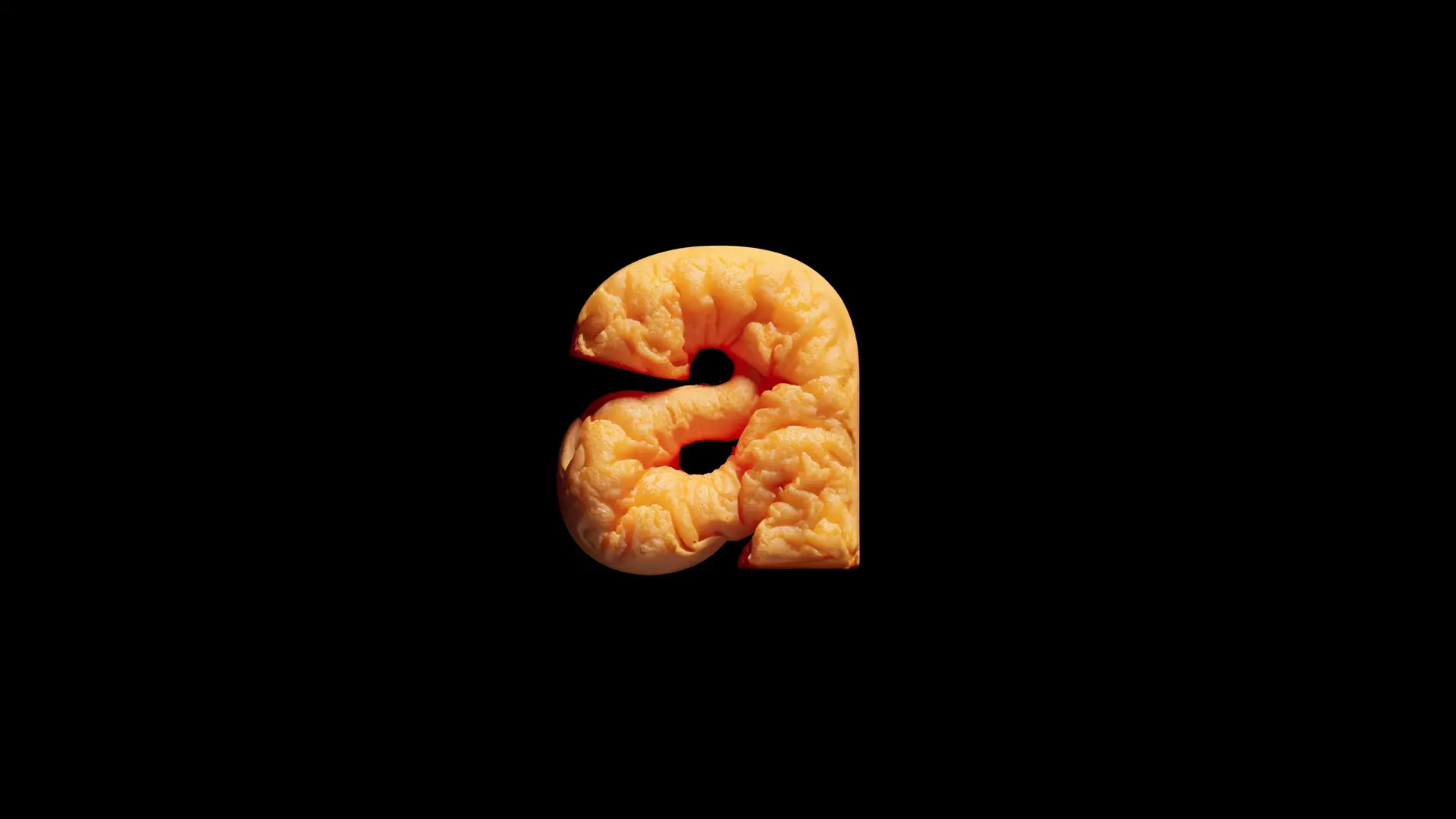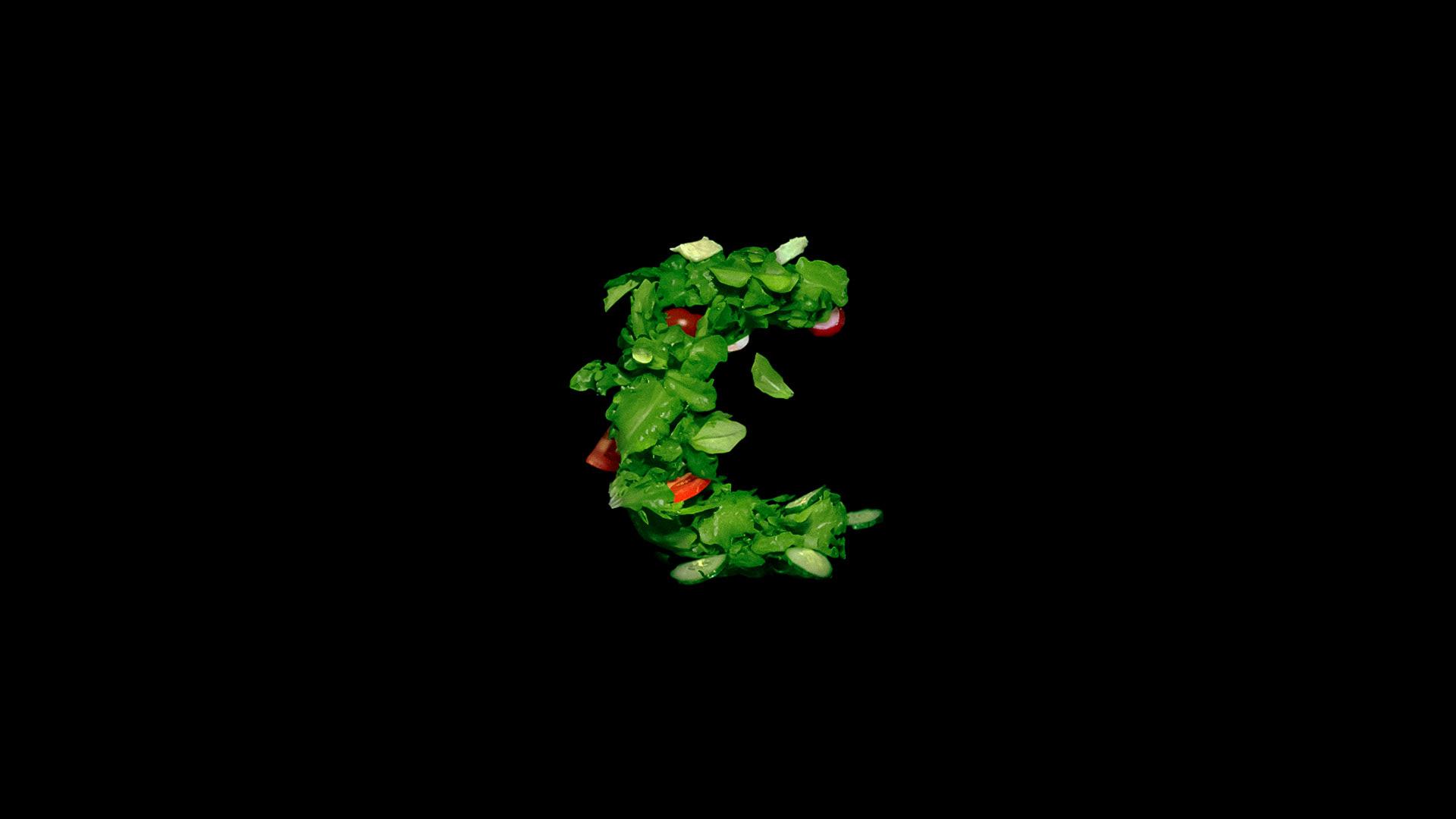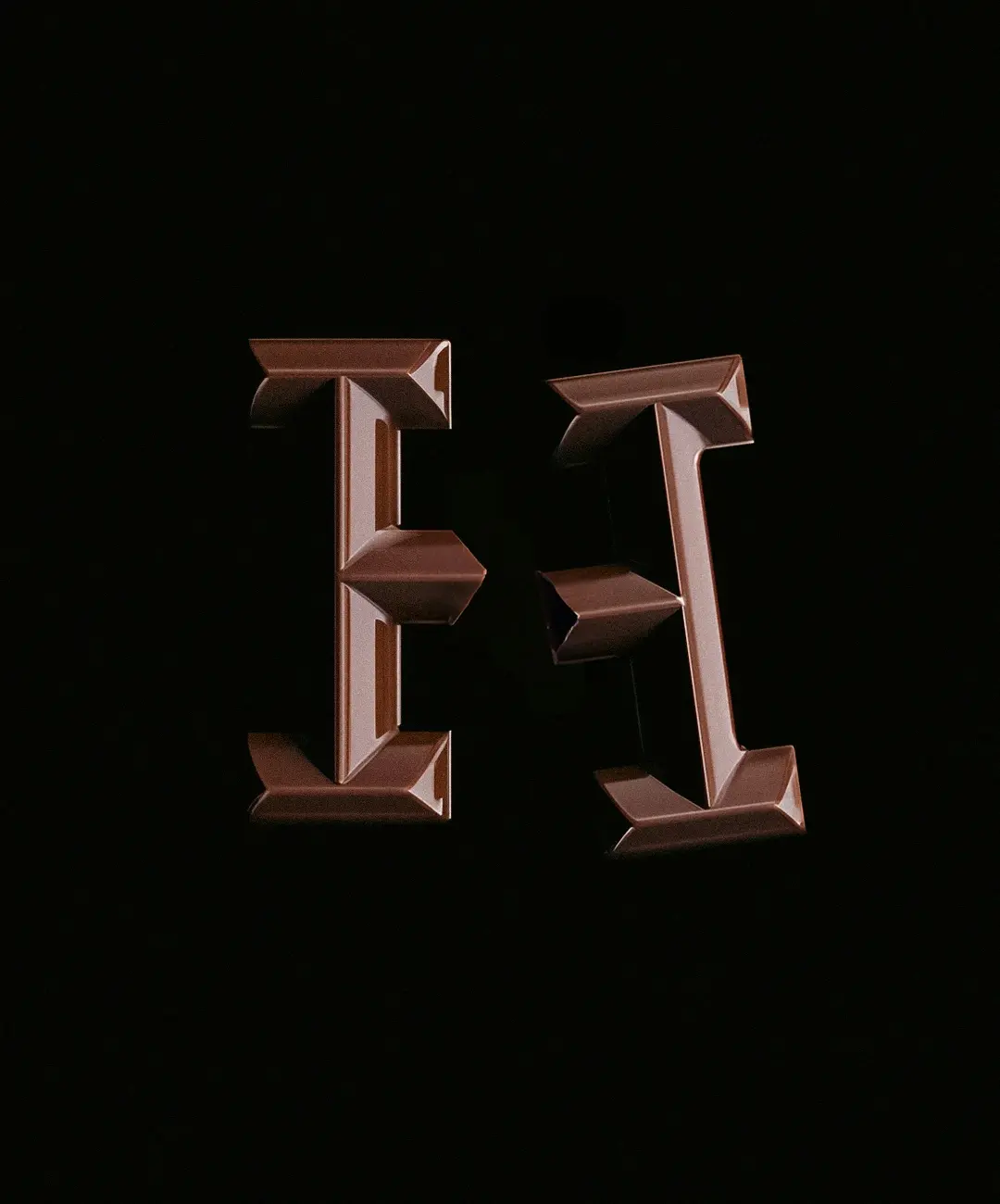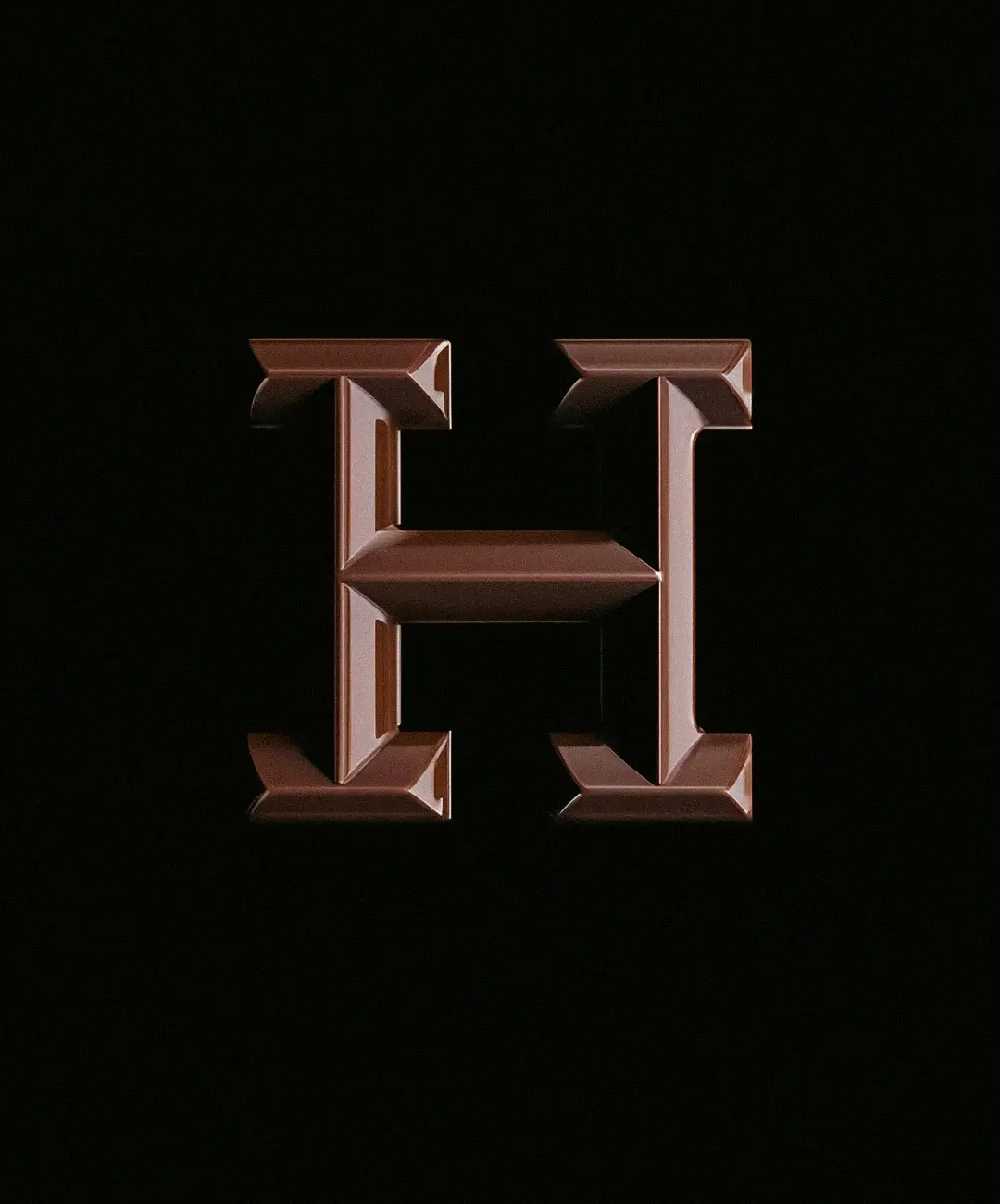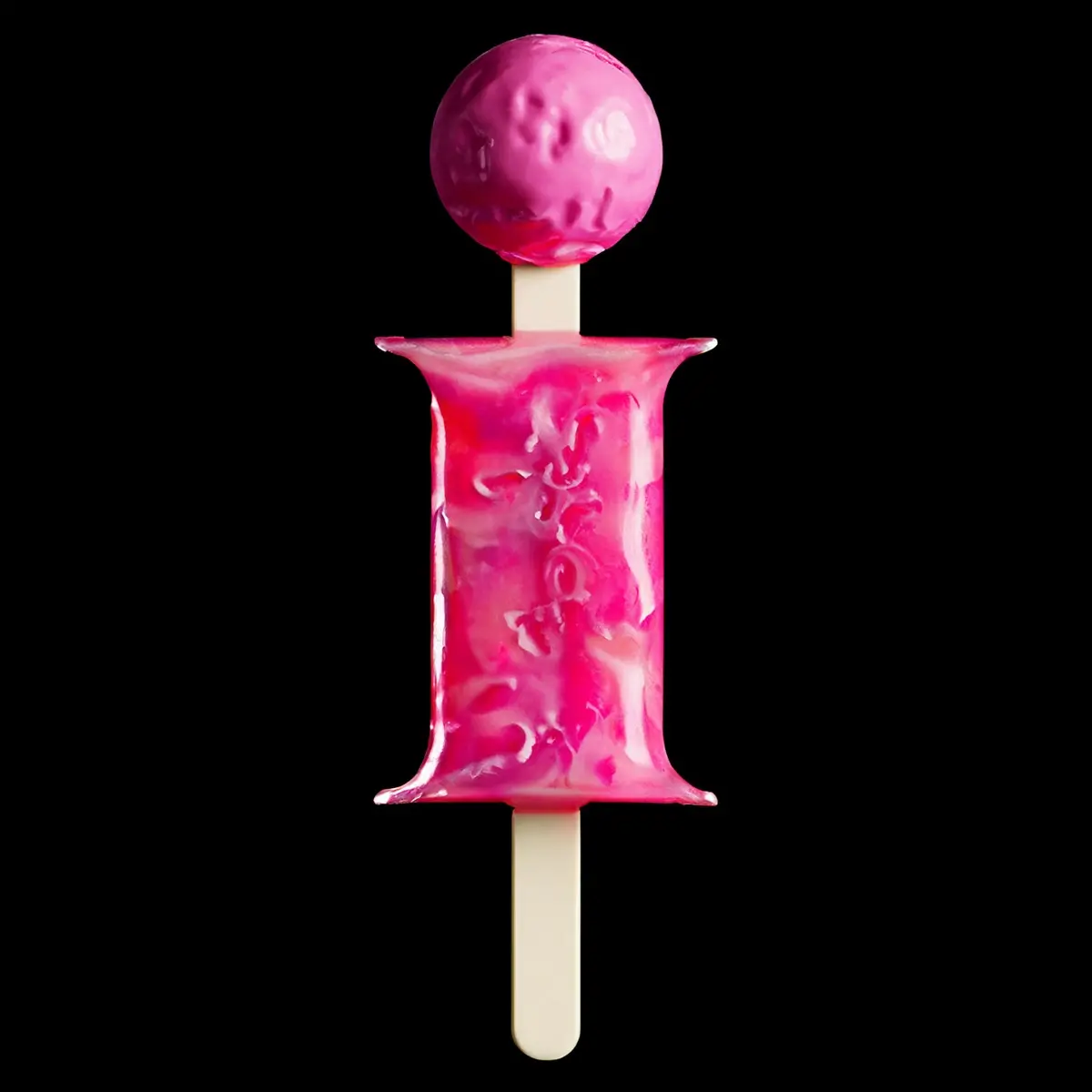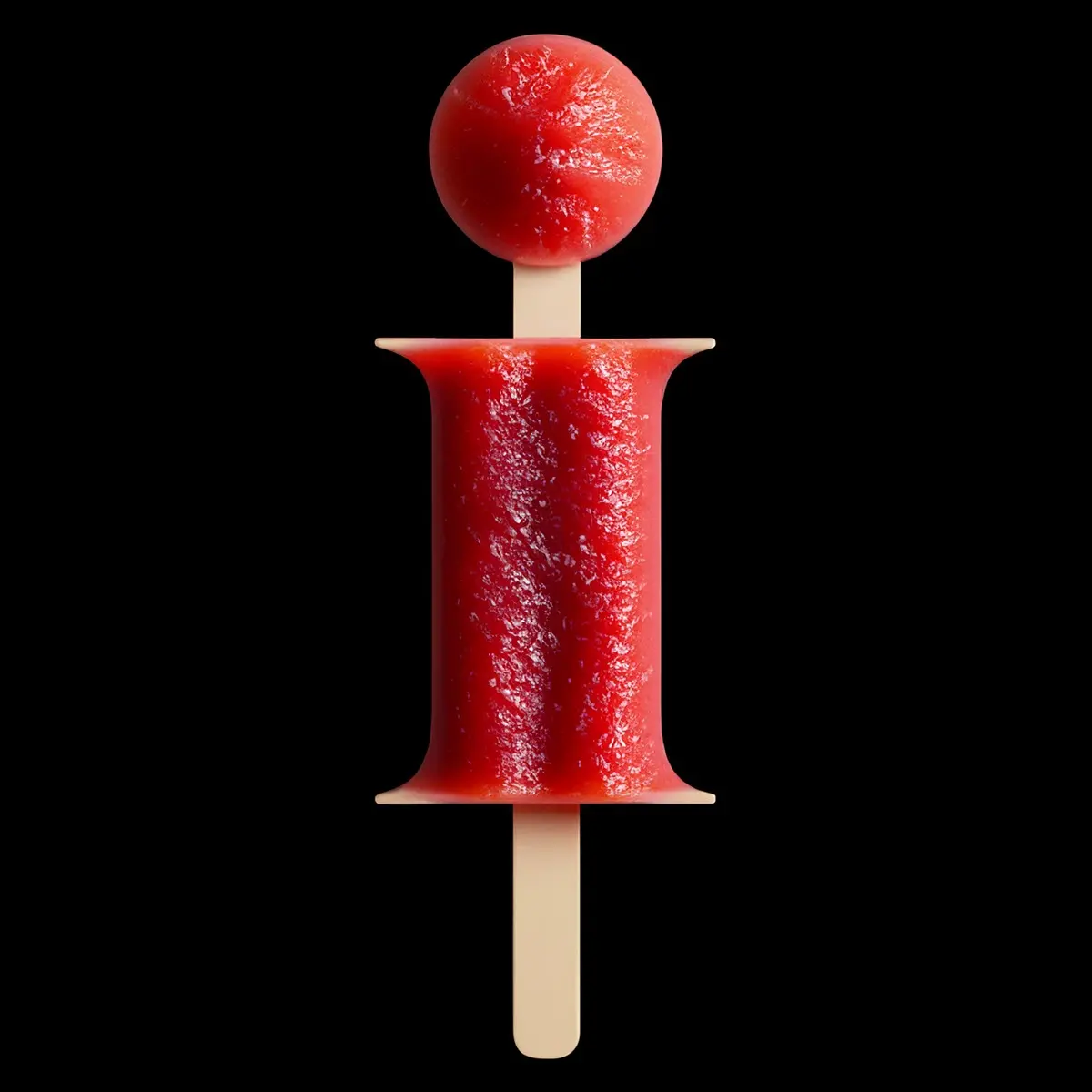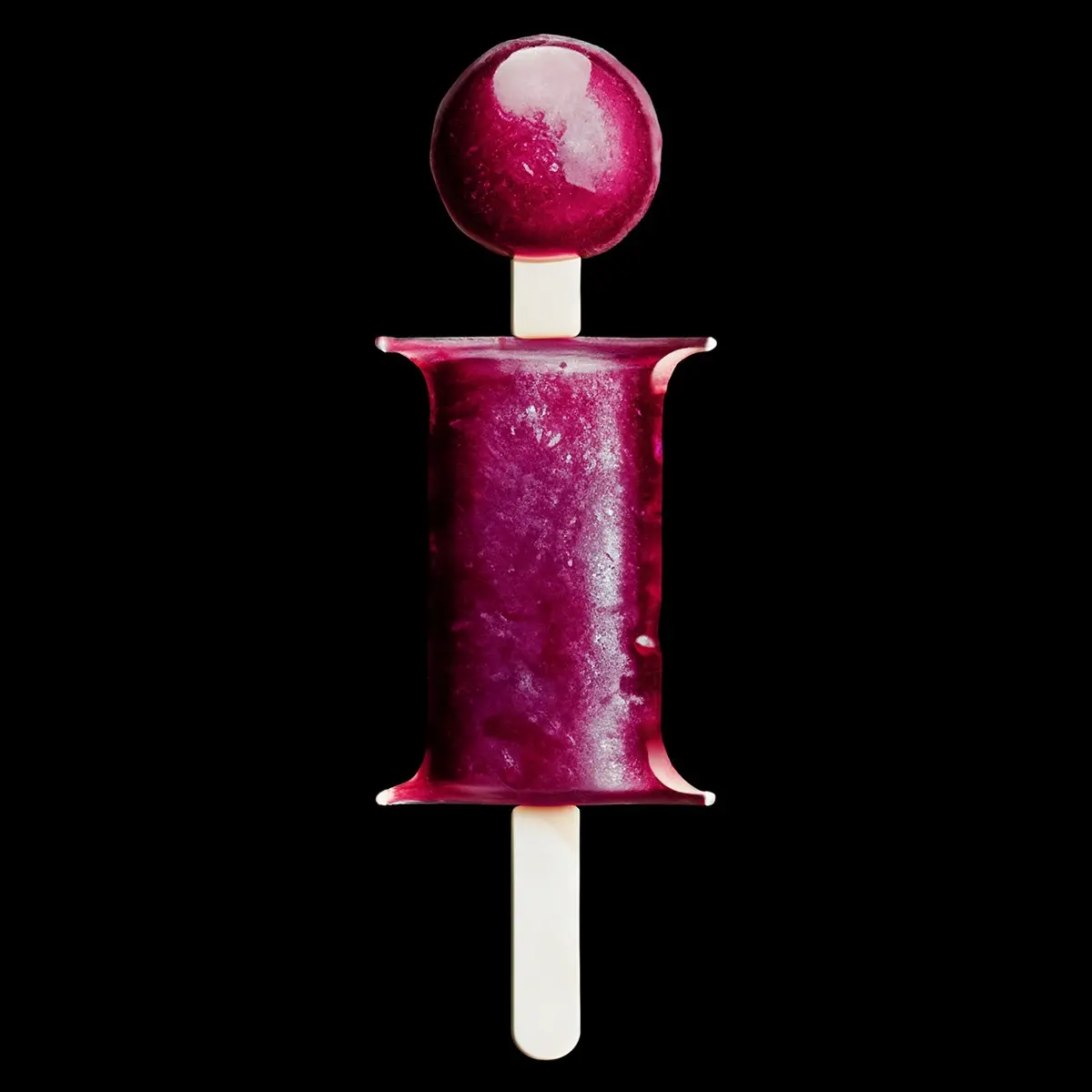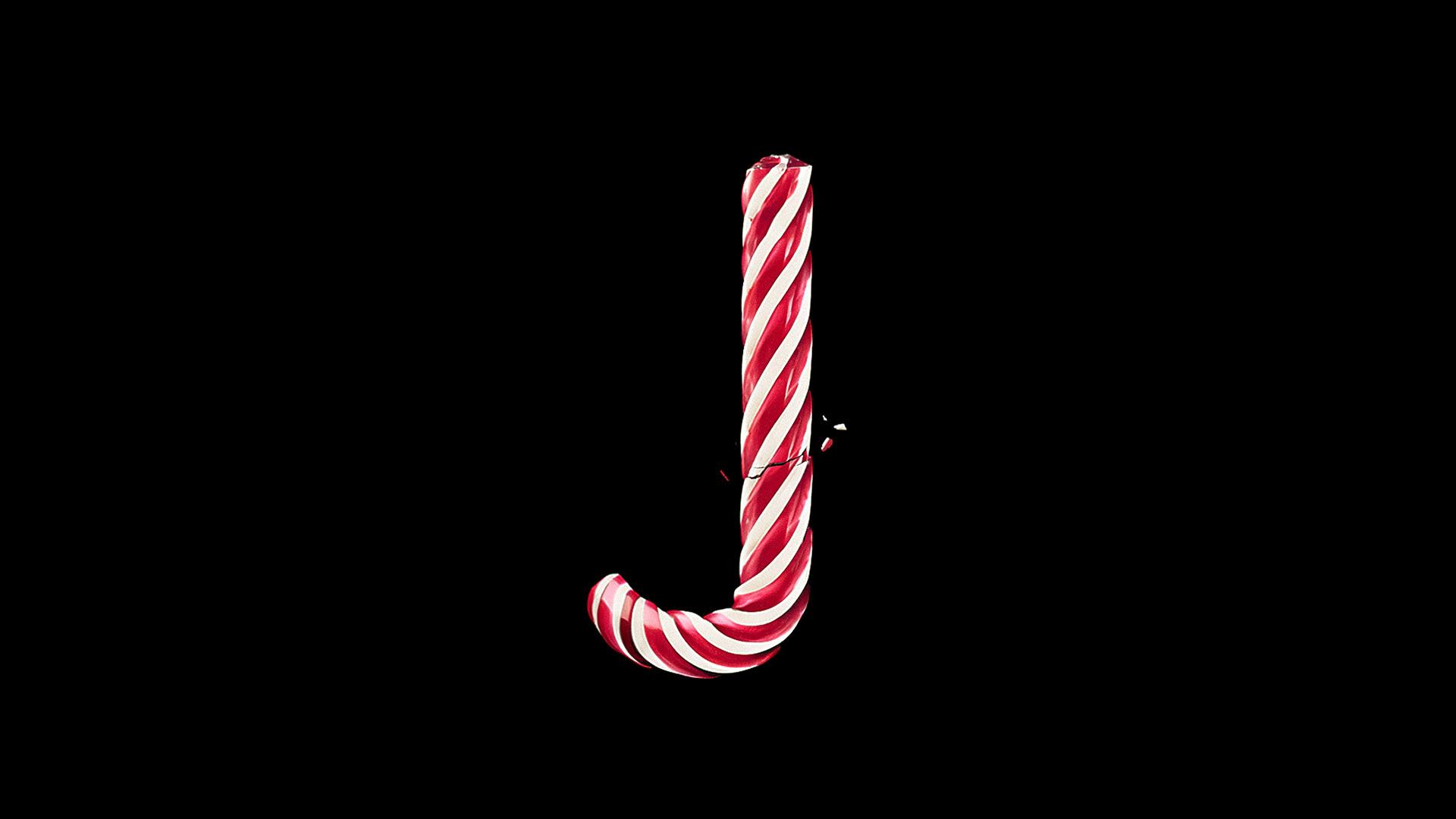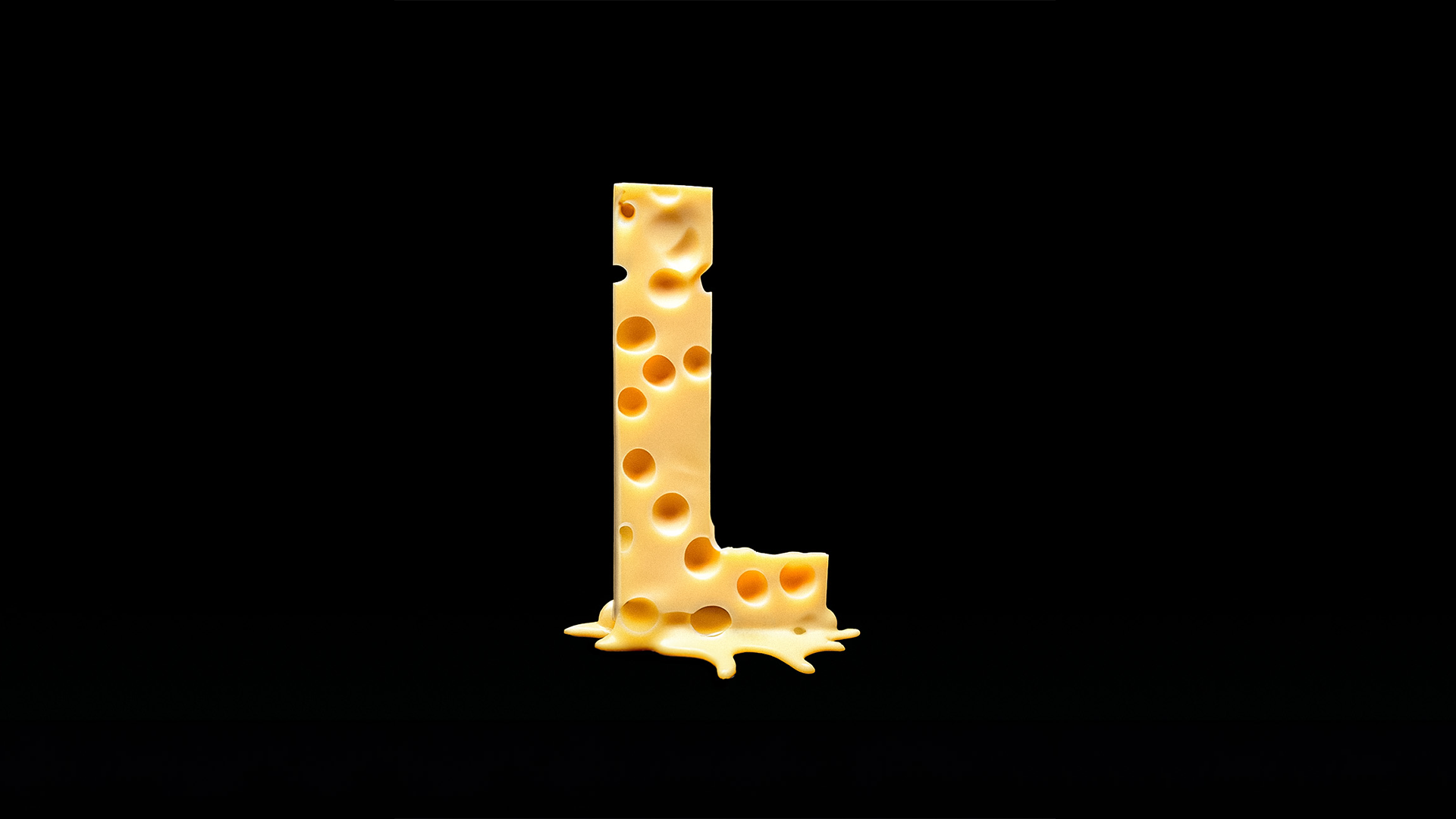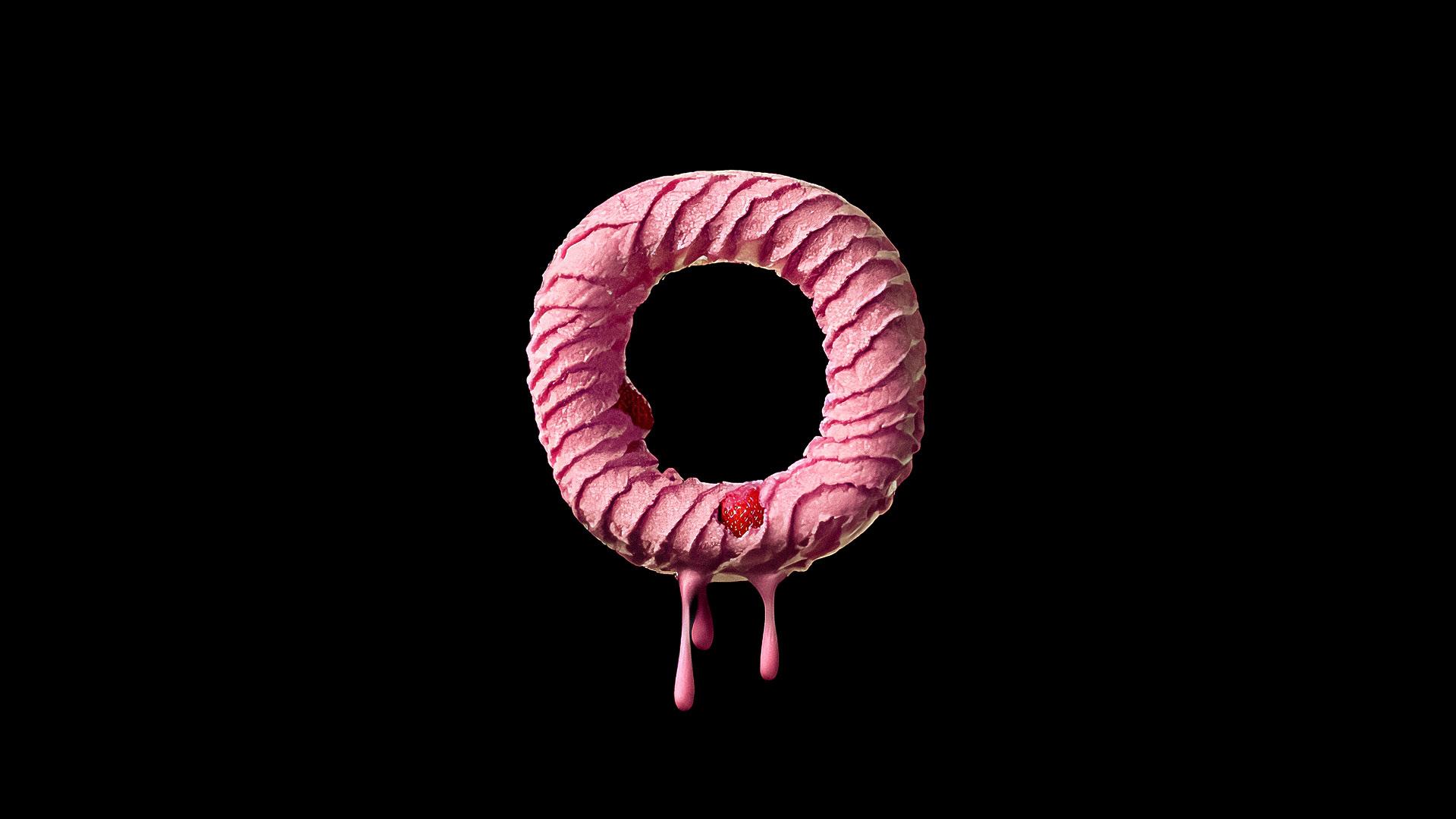
"Food Type" quand la typographie rencontre la gastronomie
Laissez-vous séduire par la créativité et l'originalité de "Food Type" - une fusion unique entre la typographie et la gastronomie qui éveillera tous vos sens!
Le studio de branding
Pang Brands est un studio créatif situé à São Paulo, Brésil, fondé par deux frères passionnés par l'entrepreneuriat. Animés par une soif de croissance et d'accomplissement, ils ont créé un studio qui croit fermement au pouvoir de transformation des entreprises, quelle que soit leur taille.
Leur spécialités
Pang Brands se concentre sur l'identité visuelle, l'image de marque, ainsi que le matériel numérique et imprimé. Ils sont passionnés par l'idée de faire émerger les meilleures idées de la table à dessin et de trouver la communication visuelle optimale pour chaque projet.
Une typo alléchante imaginée par Pang Brands
"Food Type" est une fusion intrigante de la typographie et de la gastronomie. Dans ce projet innovant, Pang Brands explore l'intersection harmonieuse entre les formes, les couleurs et les textures des aliments, en les entrelaçant avec les 26 lettres de l'alphabet. Chaque lettre devient une œuvre d'art culinaire, mettant en valeur la créativité et l'originalité du studio créatif.